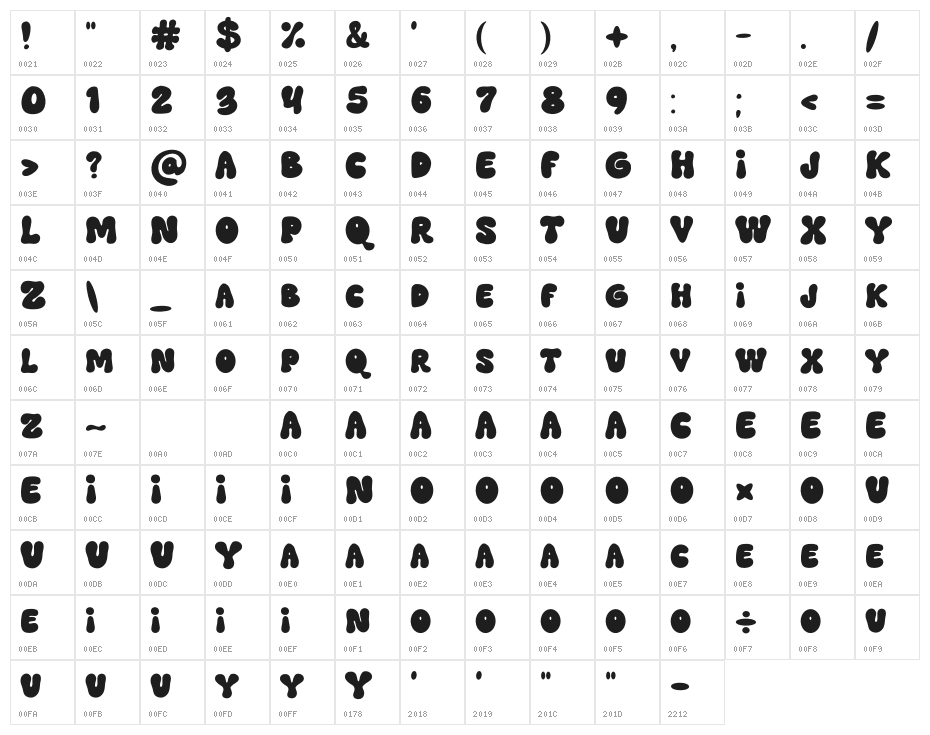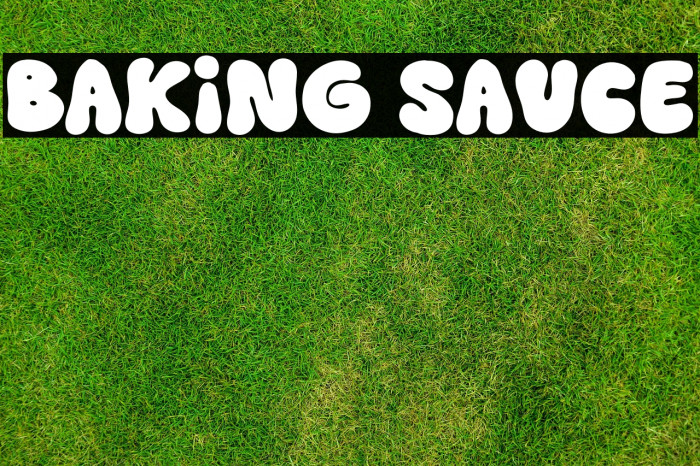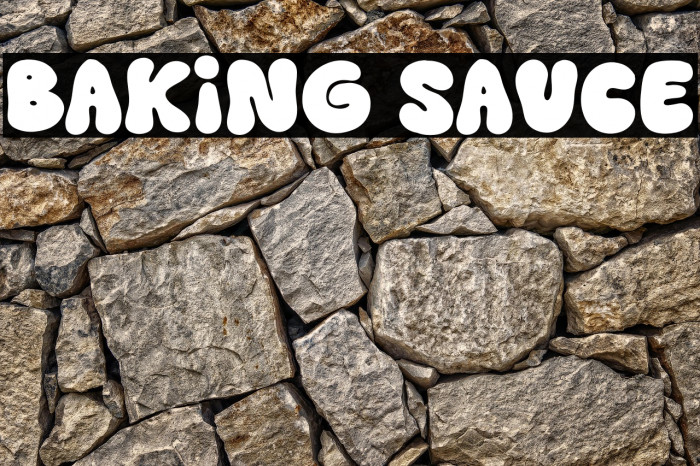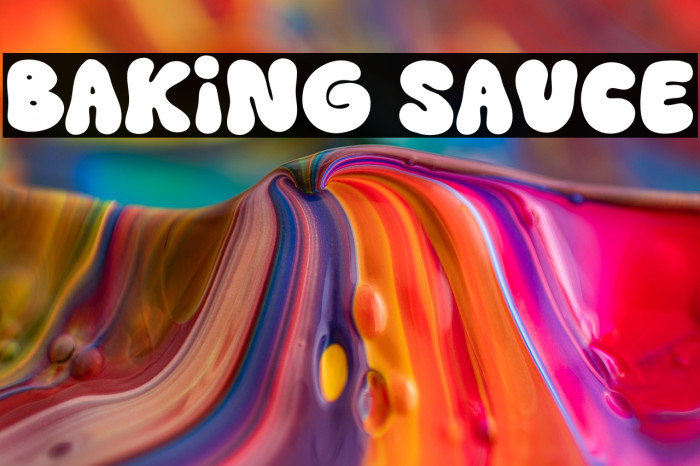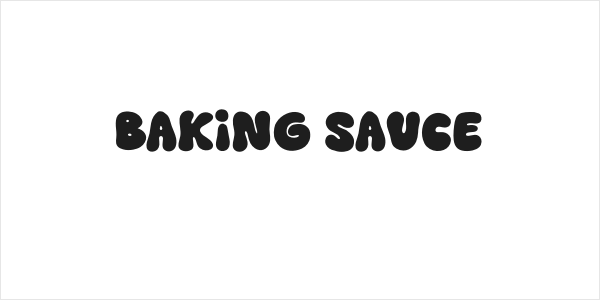
BAKING SAUCE Font
| Gesamtstil | Playful, Whimsical |
| Vorgeschlagene Projekte | Ideal for children's books, playful branding, party invitations, and any project needing a fun and lively touch. |